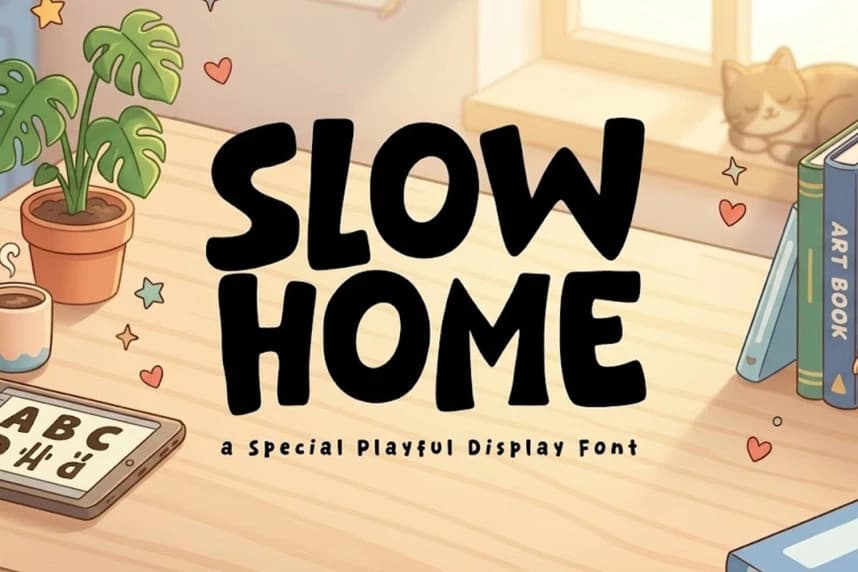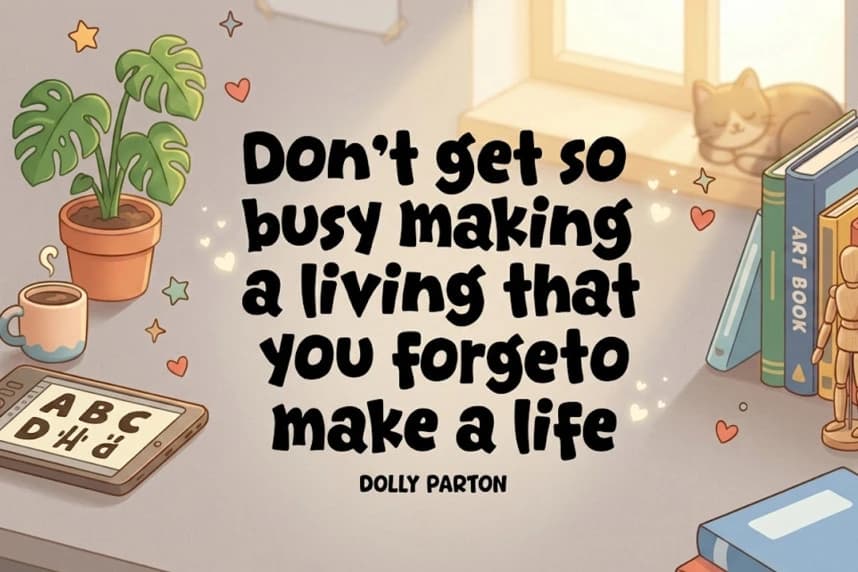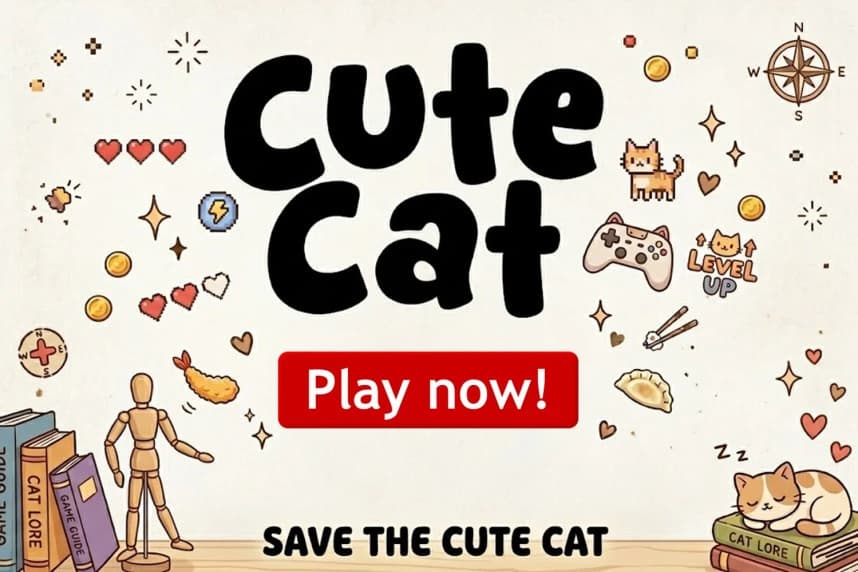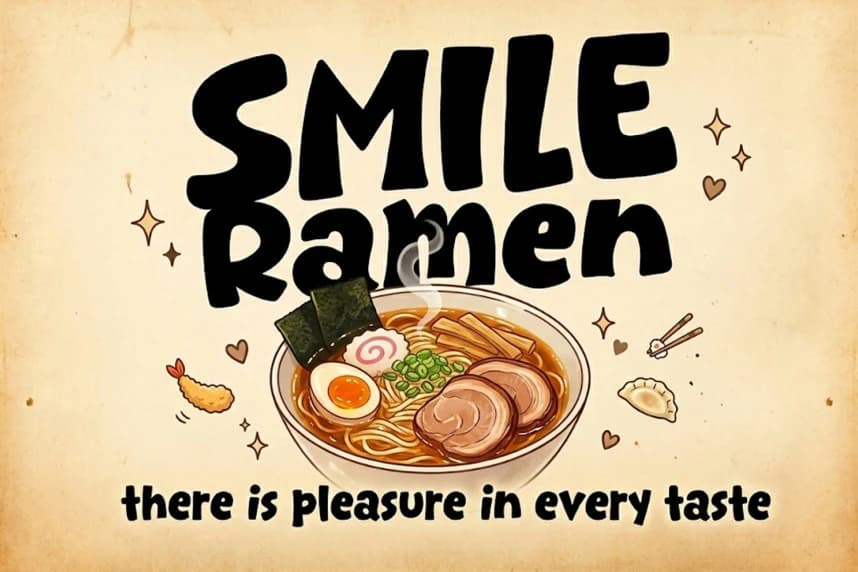
Slow Home Font
Slow Home Font, hayal gücü seven yaratıcılar için tasarlanmış cesur ve eğlenceli bir fonttur. Organik şekilleriyle ve semboller ve kesirler dahil olmak üzere tam çokdilli desteğe sahip olan bu font, işlevselliği kadar sevimlidir.
Slow Home Font, mizaha biraz düşkün olan yaratıcılar için tasarlanmış cesur ve oyunbaz bir yazı tipidir. Organik biçimleriyle ve semboller ile kesirler dahil olmak üzere tam çokdilli desteğe sahip olan bu yazı tipi, sevimli olduğu kadar işlevseldir.